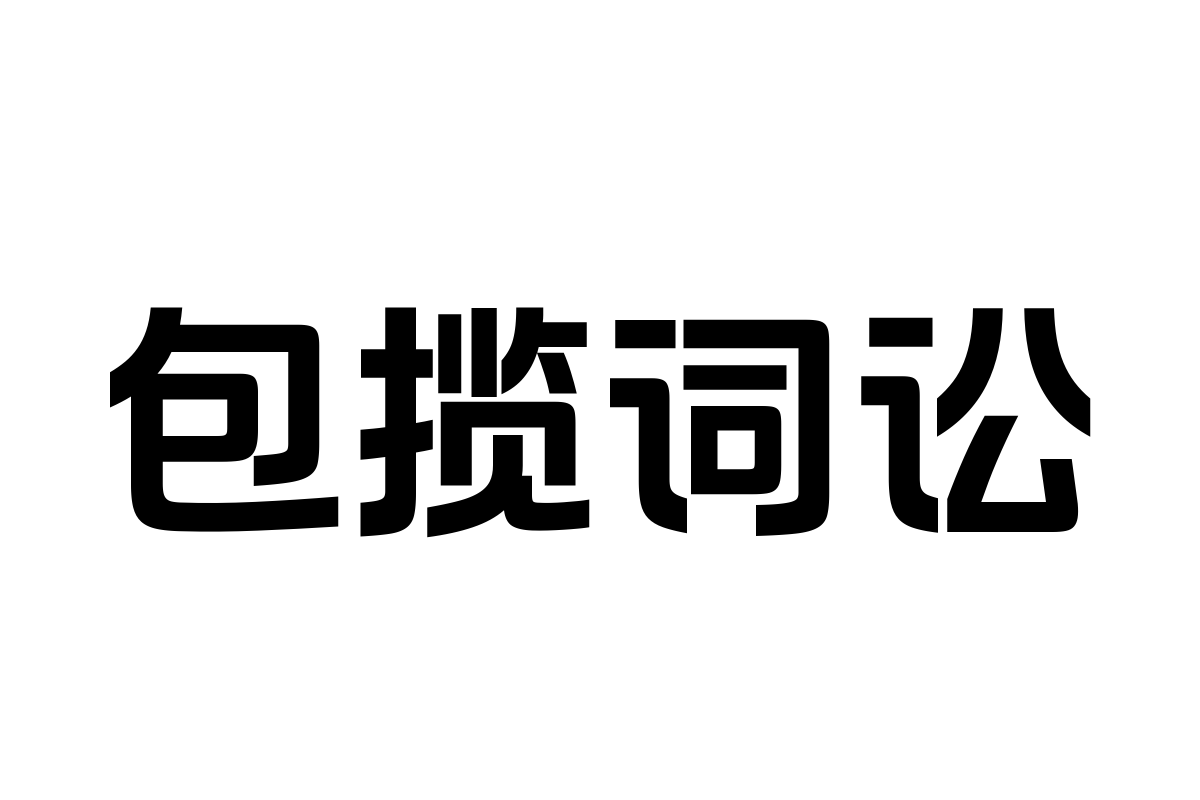
汉仪风尚黑是一款现代感十足的中文字体,由汉仪字库出品。这款字体以其简洁、大气的设计风格,广泛应用于各类商业和设计领域。
字体特点:
1. 字形规整,笔画流畅,整体风格简约而不失时尚感。
2. 线条粗细适中,既有力量感又不失细腻,适合用于标题、正文等需要突出重点的场合。
3. 字体结构紧凑,易于阅读,适合快速浏览和信息传递。
4. 适用于各种印刷和电子媒体,包括报纸、杂志、广告、网页等。
应用场景:
1. 书籍、杂志、报纸等出版物的文字排版。
2. 企业宣传册、产品说明书、海报等宣传材料的设计。
3. 网站、博客、社交媒体等网络平台的文字展示。
4. 各类商业标识、LOGO设计等。
总之,汉仪风尚黑是一款实用且具有现代感的中文字体,适用于多种设计场景,能够满足不同用户的需求。